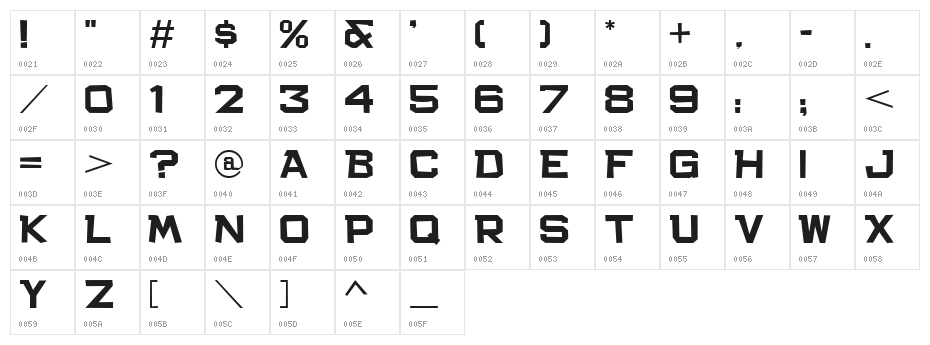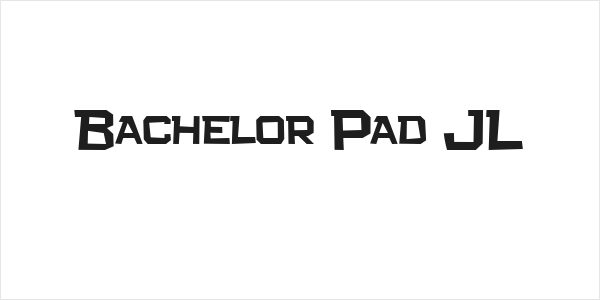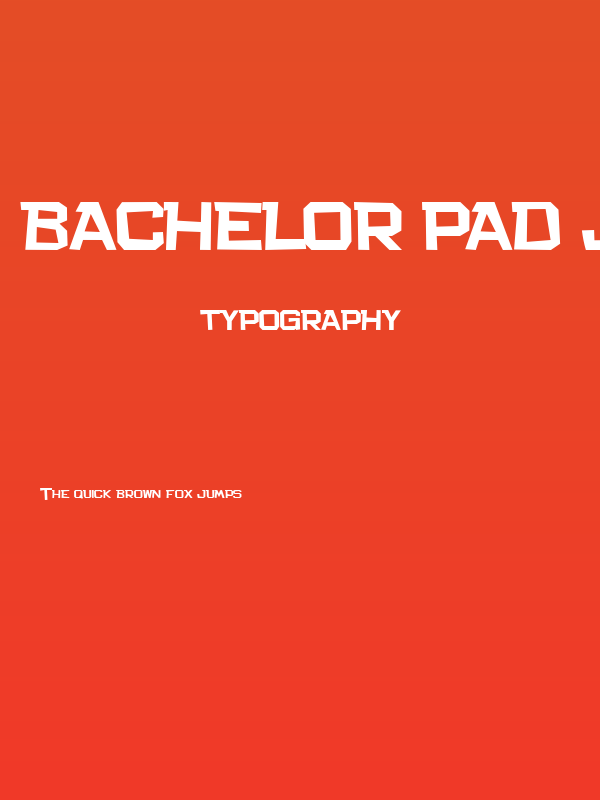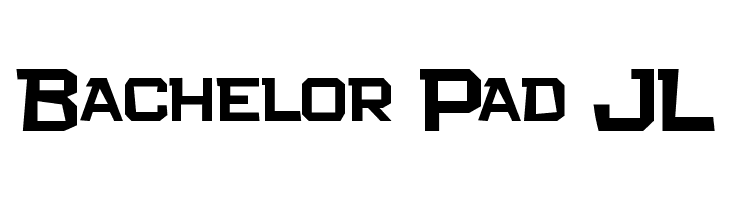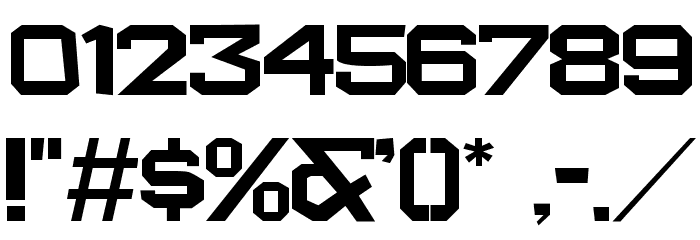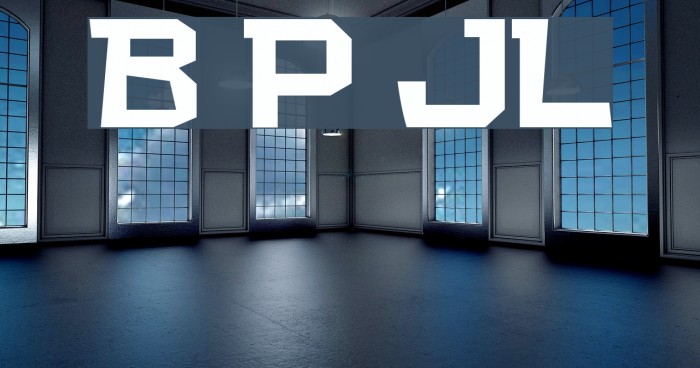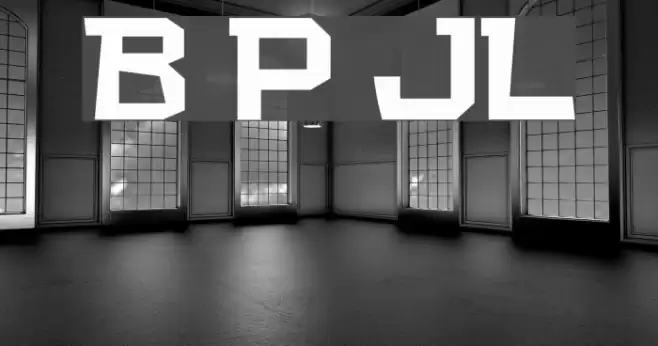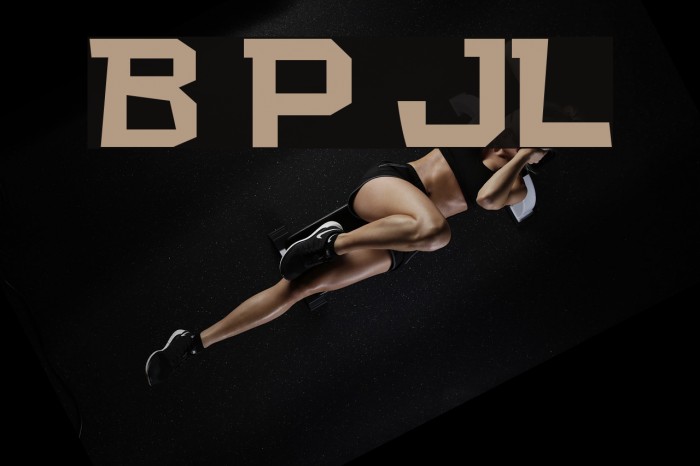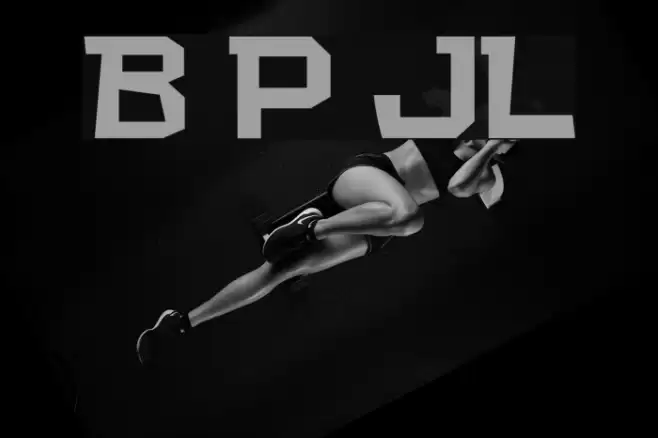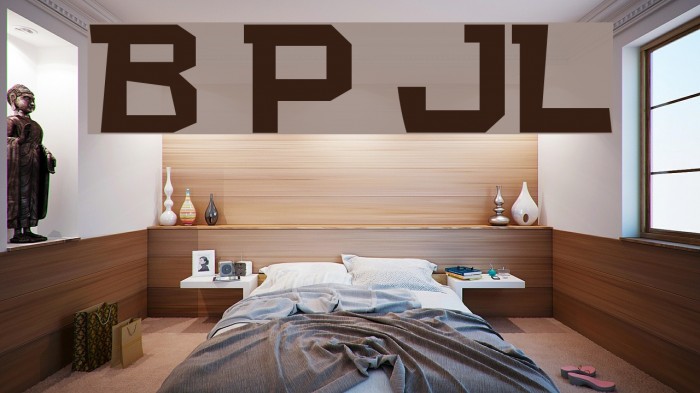
Bachelor Pad JL Font
| Projets proposés | Ideal for use in sci-fi themed designs, video game graphics, posters, and branding that requires a modern and edgy look. |